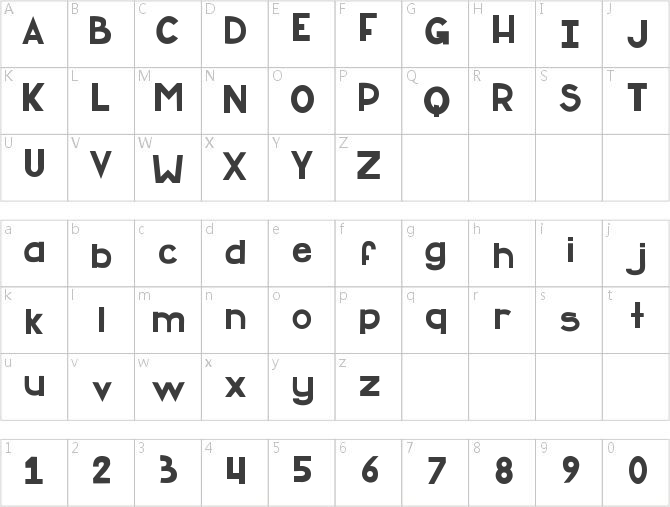
Ask-My-Flashlight
Ask-My-Flashlight字體字庫(kù)是一款讓人賞心悅目、百看不厭的英文字體,適合各類(lèi)廣告和產(chǎn)品包裝設(shè)計(jì)應(yīng)用,字體大小0.06MB,格式為ttf字體,上傳用戶(hù)是釜源貿(mào)易,作者/版權(quán)方為未知